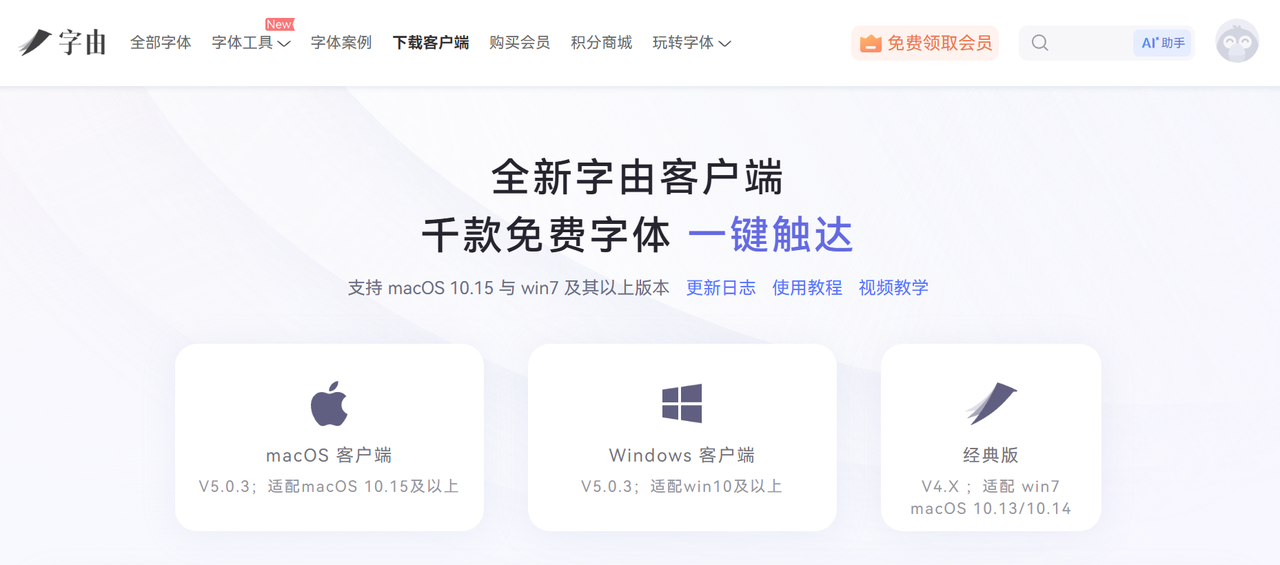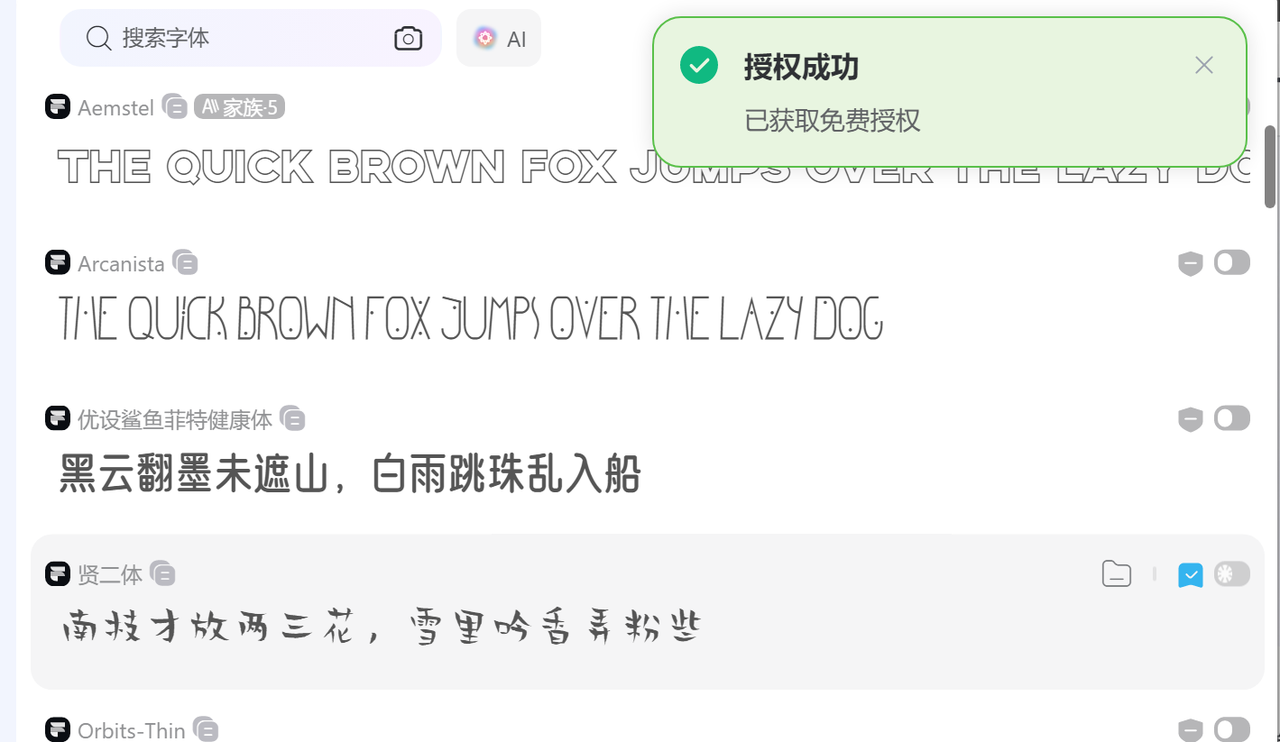
2026 最新免费字体网站推荐
无论是设计师日常做海报、剪辑师搭配视频字幕,还是职场人优化PPT排版、自媒体人打造内容辨识度,一款合适的字体总能让作品质感翻倍。但市面上字体杂乱,版权纠纷频发、优质字体收费高昂、下载后无法适配软件等问题,一直困扰着多数创作者。2026年市面上涌现出不少优质免费字体网站,既有兼顾海量资源与版权保障的综合平台,也有主打小众特色字体的垂直站点。我帮大家筛选出高适配、无套路、版权清晰的免费字体网站,让大家轻松实现用字自由,告别版权焦虑。
字由网
作为超百万设计师在用的免费字体下载工具,字由网绝非单纯的免费字体下载站点,更像是一站式字体管理与应用平台,尤其适合频繁用字的设计从业者与职场人。
字由网的免费商用字体就有3400+款,涵盖黑体、宋体、书法体、手写体、像素体等全风格,像我平时日常办公常用的简约字体,还是做设计时需要用的个性字体,都能精准匹配。更贴心的是,字体分类清晰,免费字体也会单独标注,每次我找字体的时候都是直接筛选风格,快速精准定位到自己想要的字体类型。
二、猫啃网:小众特色字体聚集地,免费商用无套路
猫啃网是主打免费字体的垂直站点,这里的免费字体更侧重小众化、风格化字体,适合想避开大众字体、打造作品独特性的创作者,所有字体均明确标注免费商用授权。站点免费字体更新频率高,2026年新增多款热门特色字体,比如基于思源宋体改造的香萃积雪宋等。
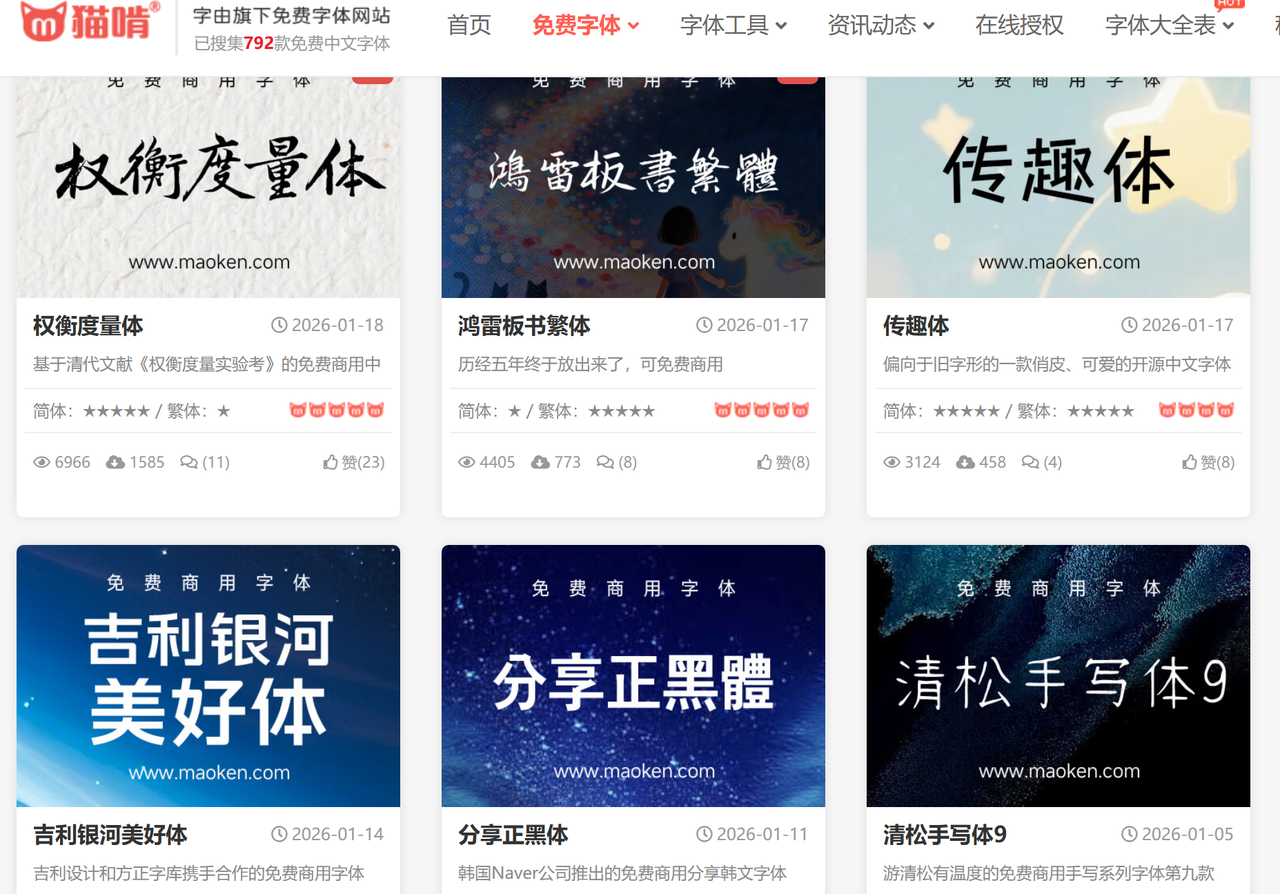
三、100font:极简无广告,免费商用字体打包下
100font也是我收藏的一款极简风免费字体网站,操作也非常便捷、字体质量高,适合讨厌繁琐流程、追求高效下载的创作者,尤其适合新手入门使用。网站收录上百款优质免费商用字体,虽数量不及字由网,但每款免费字体都经过严格版权核验,涵盖衬线体、非衬线体、手写体、卡通体等主流风格,兼顾实用性与颜值,日常办公、海报设计、自媒体排版等场景都能覆盖。
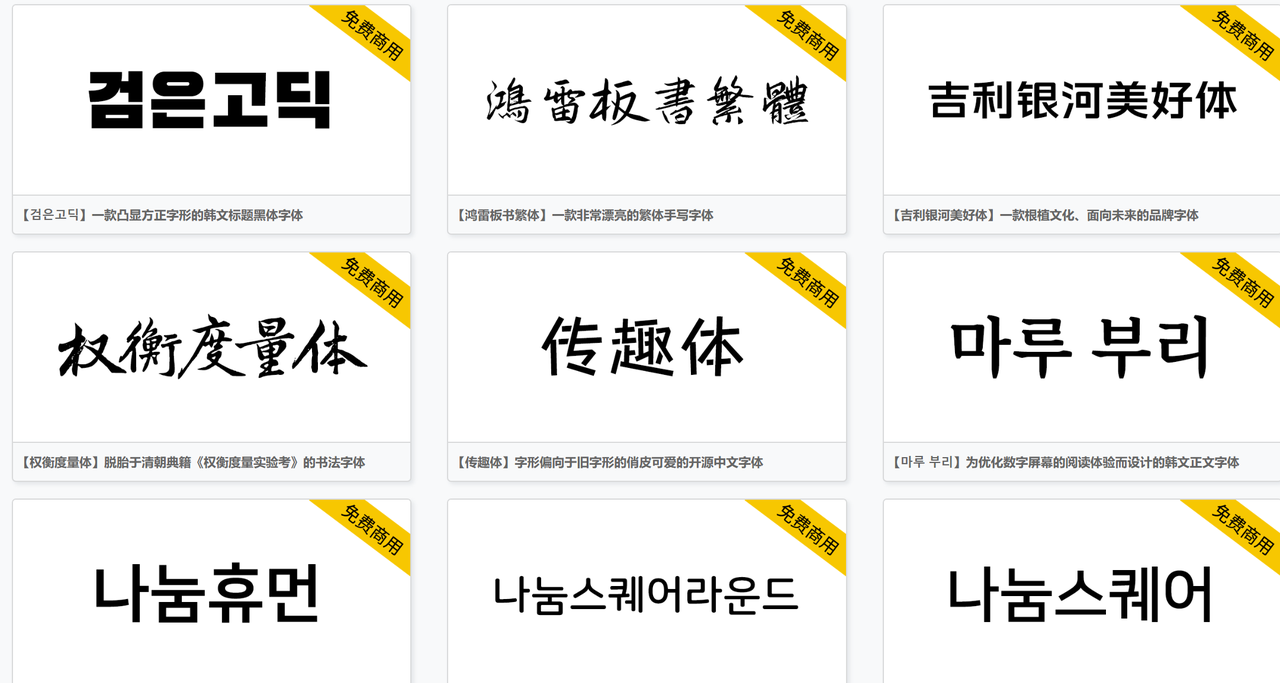
四、字体家:书法字体标杆,AI造字解锁专属风格
字体家是比较侧重书法风格的免费字体网站,同时兼顾各类实用字体,适合主打国风、非遗、传统文化类创作的创作者,免费商用字体涵盖楷书、行书、草书、隶书等多种书法字体,风格浓郁,辨识度极高。我认为这个网站的书法字体质量出众,既有经典书法字体的复刻版本,也有设计师原创的书法字体,比如多款毛笔字体笔锋凌厉,自带气势,适合品牌宣传、活动海报设计。